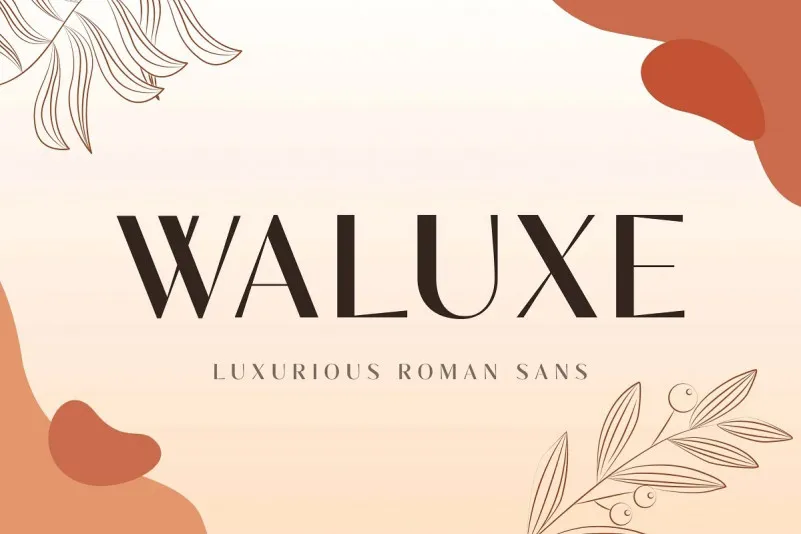
Esta fonte é um tipo elegante que combina sofisticação com minimalismo. Desenvolvida pelo designer de fontes Almarkha Type, esta é uma fonte do tipo sans-serif leve e alta contraste ideal para a criação de templates, brochuras, vídeos, embalagens publicitárias, logotipos e muito mais. Suas linhas sutis e forte contraste criam um visual moderno que se adaptará perfeitamente à sua necessidade de design, oferecendo uma maneira única de estilizar seu conteúdo. A Waluxe Font é a escolha ideal para quem busca um estilo clean e moderno para seus projetos visuais.